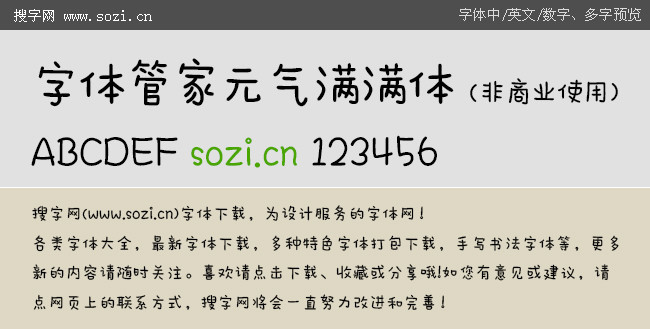
字體管家元氣滿滿體(非商業(yè)使用)
搜字網(wǎng)給大家提供一款字體管家元氣滿滿體(非商業(yè)使用)中文字體下載,該字體是一款個性的藝術(shù)字體,字體樣式可愛,富有趣味。適合兒童包裝畫冊、書籍海報等廣告設(shè)計應(yīng)用(此字體為個人非商用版,商用可以聯(lián)系QQ:1006760504)。